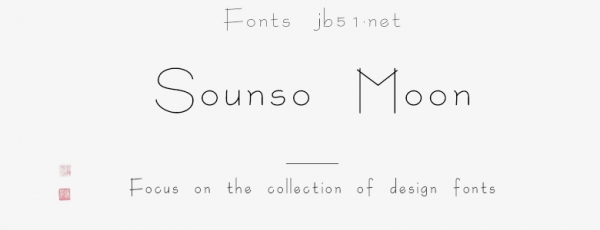
Sounso Moon是由上首造字出品的英文字體,這款字體筆劃修長(zhǎng),整體風(fēng)格偏向于手寫(xiě)體,通過(guò)大小寫(xiě)的大小變化差異使其風(fēng)格顯得更加生動(dòng)活潑更具現(xiàn)代感,適合應(yīng)用于藝術(shù)設(shè)計(jì)、平面宣傳設(shè)計(jì)、網(wǎng)頁(yè)設(shè)計(jì),書(shū)法字帖等領(lǐng)域。